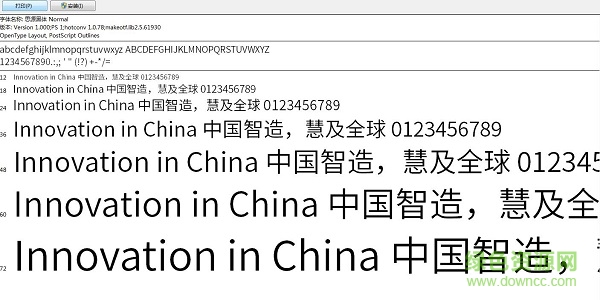
思源黑体normal字体
思源黑体normal字体是一款可以适应屏幕用字需求的高品质黑体字体,字面开阔,整体结构协调,识别度高,用在正文排版、网页设计、平面设计等领域都能可以,感兴趣的朋友快来下载吧!
字体特点
1.不但适用于印刷媒介,还可用于屏幕阅读;
2.撇、捺、钩笔画的粗细变化不大;
3.美观大方,应用范围广等。
sourcehansanssc normal字体
字体笔形介绍
字体的笔形相对于某一规定的字体是不能改变的,宋体就是以一套宋体的笔形构成,黑体就是以—套黑体的笔形构成,但相对于创意性个体,就可以根据不同创意源点进行变换,通过种种变换手法的处理,往往能带来别具一格的新型字形。变换笔形的方法有多种,如突变、无理旋转、叠加、过度变换、互衬。